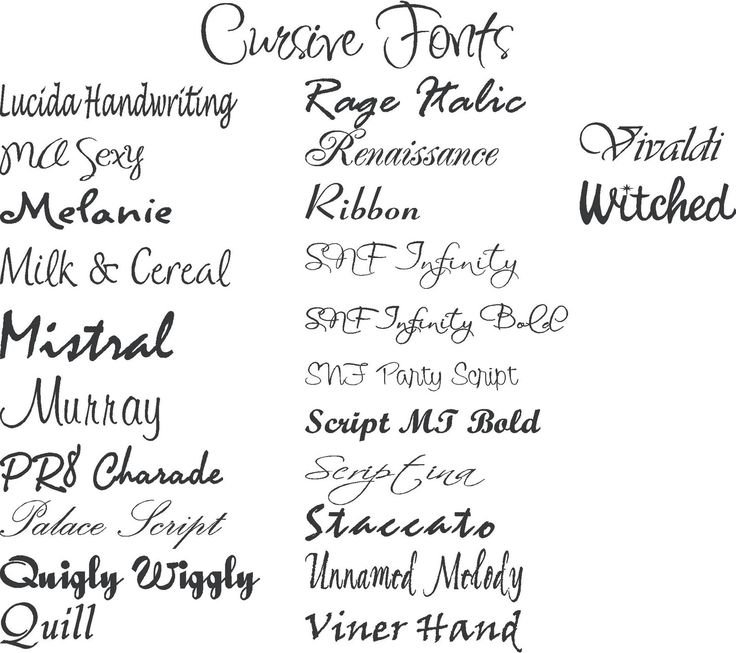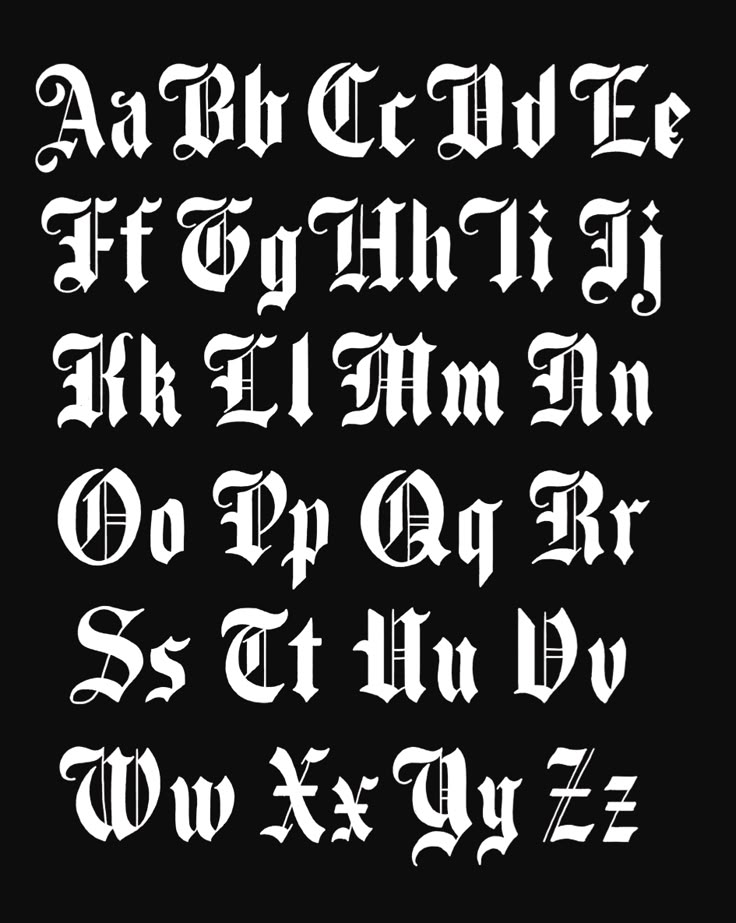
Тату в стиле леттеринг для девушек и парней.
Татуировки так же уникальны, как и люди, которые их носят. Хотя многие дизайны имеют похожие элементы, такие факторы, как личный стиль художника, его положение и тип кожи клиента, играют определенную роль в результате.
Некоторые люди предпочитают слова картинкам. Если это вы, то шрифт или буквы сами по себе добавляют еще больше смысла выбранным вами словам. Тату-шрифты — это стили, доступные для надписей. Есть тысячи вариантов на выбор, и каждый добавляет словам свой индивидуальный стиль. Кроме того, слова и высказывания прекрасно подходят для вдохновения людей и это также может служить напоминанием о том, как жить спокойно своей жизнью. Некоторые даже доходят до цитирования латинских слов и библейских стихов.
Некоторые факторы, о которых стоит подумать:
- Тип шрифта (форма букв).
- Стиль шрифта (жирность, угол, размер и т.
Д.). - Вам нужен шрифт с засечками (где буквы имеют небольшие расцветки) или без засечек (более простая линия)?
- Как текст будет соответствовать той части тела, на которой он отображается?
- Кернинг (регулировка расстояния между буквами, чтобы повлиять на читабельность и художественность дизайна).
- Вы хотите, чтобы слова были выделены или затенены, чтобы они действительно выделялись?
- Дополнительный графический контент.
- Сплошной, растушеванный или затененный цвет?
- Какими еще визуальными способами можно подчеркнуть сообщение или смысл, которые вы пытаетесь передать?
Почему стоит выбрать татуировку с текстом? Вы можете выбрать слова, чтобы:
- Отпраздновать рождение ребенка
- Отображать любимые девизы, цитаты и поговорки
- Выделите важные имена и даты
- Чествуйте личные годовщины или торжества
- Проявлять чувства
- Всегда помнить о близких, которых нет рядом (Мемориальная татуировка)
Плотные тату надписи
Плотные тёмные чёрные буквы часто используются для создания заявления.
Как же сделать желаемый дизайн ? — Просто
— Генератор шрифтов татуировки
Генератор шрифтов для татуировок — отличный инструмент для создания текстовых татуировок. В Интернете доступно множество различных бесплатных инструментов, если вы просто выполните поиск в Google. Некоторые из них загружаются, некоторые — просто онлайн-приложения.
Просто введите слово или фразу в онлайн-инструмент, а затем выберите шрифт в раскрывающемся меню. Отличный способ быстро и легко просмотреть свою татуировку! Когда вы найдете идеальный шрифт, просто распечатайте его и принесите своему художнику.
Всегда проверяйте грамматику и правописание
Самое важное, что вы должны помнить при татуировке слов на теле — проверять орфографию и грамматику.
Если бы каждый татуировщик был честен, все они признались бы, что неправильно написали что-то в какой-то момент своей карьеры, поэтому вам нужно убедиться, что слова правильные.
Вы несете полную ответственность за проверку грамматики и правописания на новой татуировке. Вы собираетесь носить его, поэтому постарайтесь избежать главной ошибки навсегда.
Формулы, уравнения и математические символы в виде татуировок
Математические формулы и уравнения — отличный выбор, особенно для математиков, ученых и гиков.
Пи (с любым десятичным числом).
Любимое уравнение или формула. Например, Эйнштейна, Ньютона, Эйлера или Шредингера.
HTML или другой код.
Текстовая татуировка — это просто?
Хотя письмо и текст — одни из первых навыков, которым обучают татуировщика, они также являются одними из самых технически сложных. Чтобы цитата выглядела потрясающе, она должна быть одинаковой по размеру и стилю и отображаться прямо на пышном холсте — вашем теле. Для этого требуются практика и талант, которые есть у наших мастеров)
Некоторые работы наших мастеров в стиле леттеринг
Тату-шрифты — Последователи ▷➡️
Тату-шрифты. к генерировать новые шрифты для Instagram откройте платформу, напишите или вставьте фразу, просмотрите его в разных стилях, скопируйте отрывок с нужным шрифтом и вставьте текст в Instagram, Facebook, Твиттер, Youtube, WhatsApp, Twitch, TikTok или любую социальную сеть.
Есть и другие сайты, которые также предлагают эту услугу.
Поскольку Instagram Stories предлагает некоторые возможности, когда мы пишем описания, комментарии или сообщения, нет возможности, кроме шрифта по умолчанию.
Тем не менее, есть сторонние инструменты которые предлагают пользователям возможность размещать другие источники. Продолжайте с нами, чтобы узнать больше об этой альтернативе и узнать, как применяйте шрифты, которые делают ваши публикации более привлекательными, в данном случае шрифты для татуировок.
У Followers Online очень простая страница, только точная поместите свой текст чтобы узнать, как обстоят дела с пользовательскими шрифтами. Позже, просто скопируйте и вставьте в его Instagram.
Тату-шрифты. Если вам нужны дополнительные параметры для оформленного текста, просто нажмите «загрузить больше шрифтов». Появляющиеся здесь возможности более случайны, отходят от стандарта и объединяют ресурсы, имеющие мало общего, emojis y Символы.
для татуировок доступны и имеют множество различных шрифтов на выбор. Эти веб-сайты шрифтов позволяют людям выбрать именно тот тип шрифта, который необходим для татуировки. Веб-сайты генераторов шрифтов также доступны для людей, чтобы разработать идеальный шрифт для татуировок, что дает людям возможность создать стиль шрифта, который может быть уникальным только для них самих.